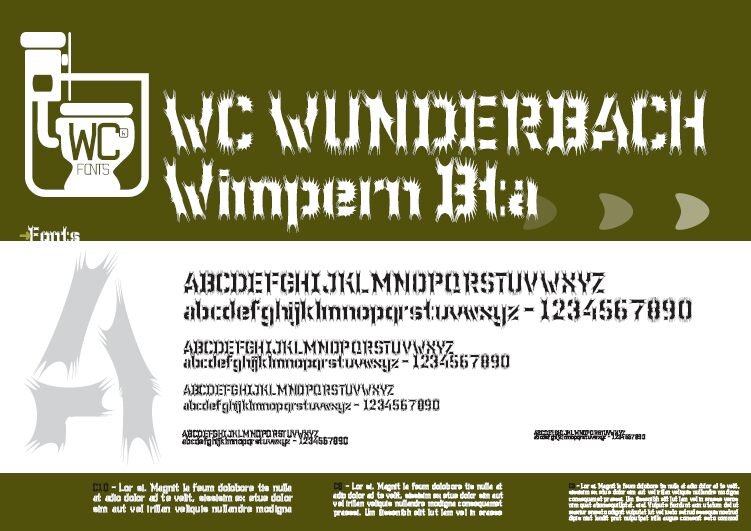
WC Wunderbach Wimpern
WC Wunderbach Wimpern od WC Fonts to darmowy, zniekształcony font horrorowy typu display. Jego litery wyglądają jak zarośnięte ostrymi rzęsami i poszarpanymi cierniami. Ciemna sylwetka robi tu największą robotę: wysokie, nierówne pociągnięcia i najeżone krawędzie nadają krojowi dziki, drzazgowaty rytm – bliższy zdrapanej korze czy przypalonemu futru niż uporządkowanym literom.
Ten klimat pasuje do tytułów plakatów, okładek albumów, ulotek na Halloween, logotypów gier i nagłówków zinów, gdzie słowo musi sprawiać wrażenie nieokiełznanego, zanim jeszcze zostanie przeczytane. Jako darmowy font najlepiej sprawdza się w krótkich formach – planszach tytułowych, hasłach na okładkach i znakach graficznych – ponieważ te "pazurzaste" kontury budują mocną teksturę nawet przy kilku literach.